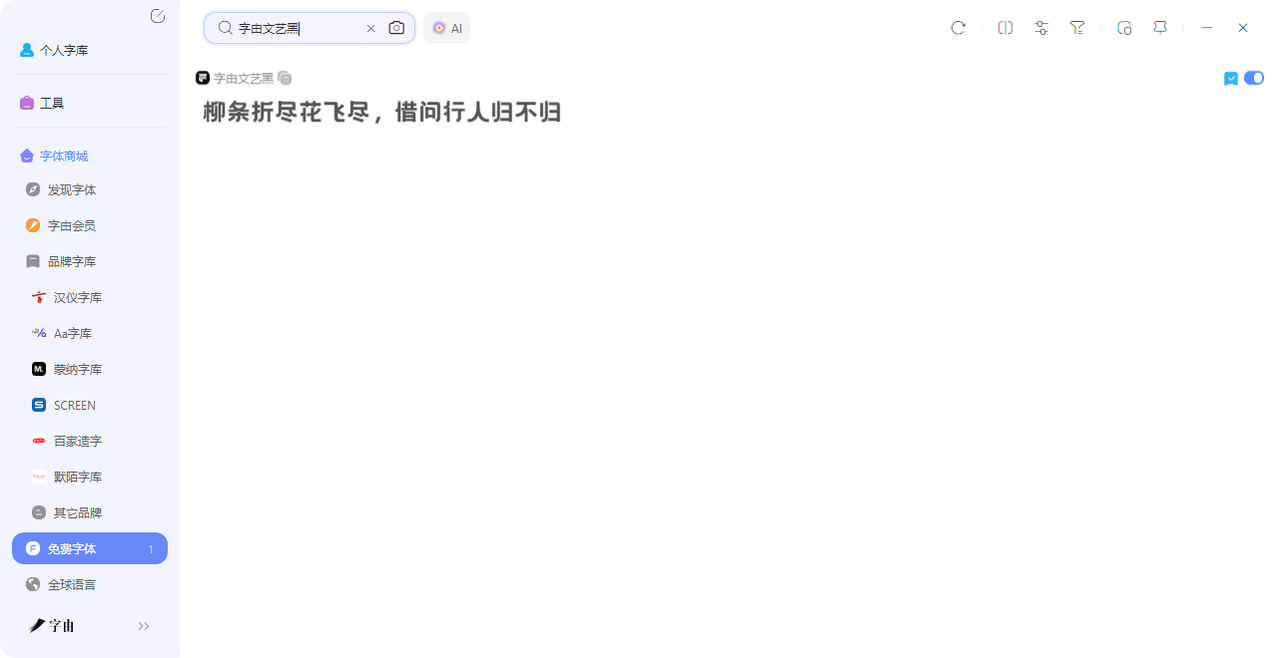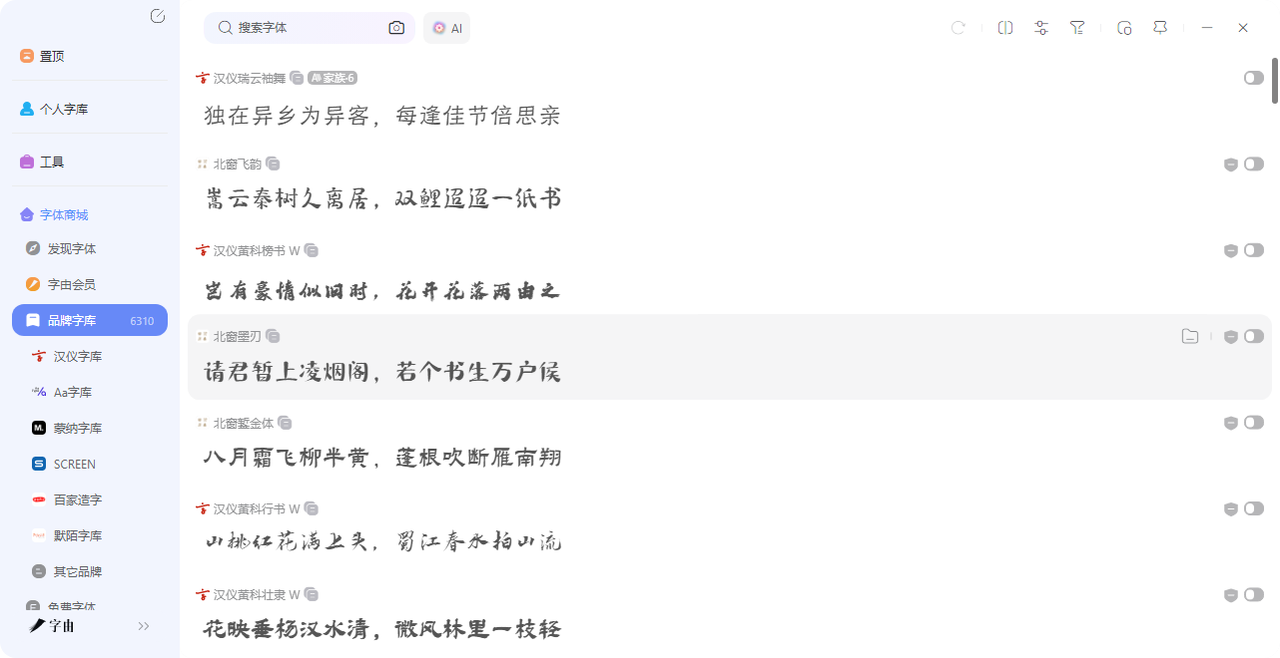
别再一个个下字体了!这几个打包下载网站直接收藏
做设计的人都知道,最烦的不是找字体,而是找着了之后一个一个下,麻烦的话还要给字体做收纳整理,遇到那种一个字体包里有好几个字重的,还得重复操作好几次。折腾半天,电脑里是多了几十款字体,但是时间也没了。其实,现在有不少网站支持字体打包下载,一次就能把整套字体收进电脑。今天我就把私藏的6 个字体打包下载网站分享出来,从国产神器字由到国外精选平台,每个都能让你省下大量时间。需要的直接收藏,以后下字体不用再一个个点。
很多人用字由,习惯一款一款点着用,但其实它有个更省事的思路——你不用下载,直接“打包用”。
字由的客户端里,目前已经有了3585 款免费商用字体。你不需要把每个字体文件下载到电脑里,而是打开客户端,选好字体,在PS 里点一下就能用。
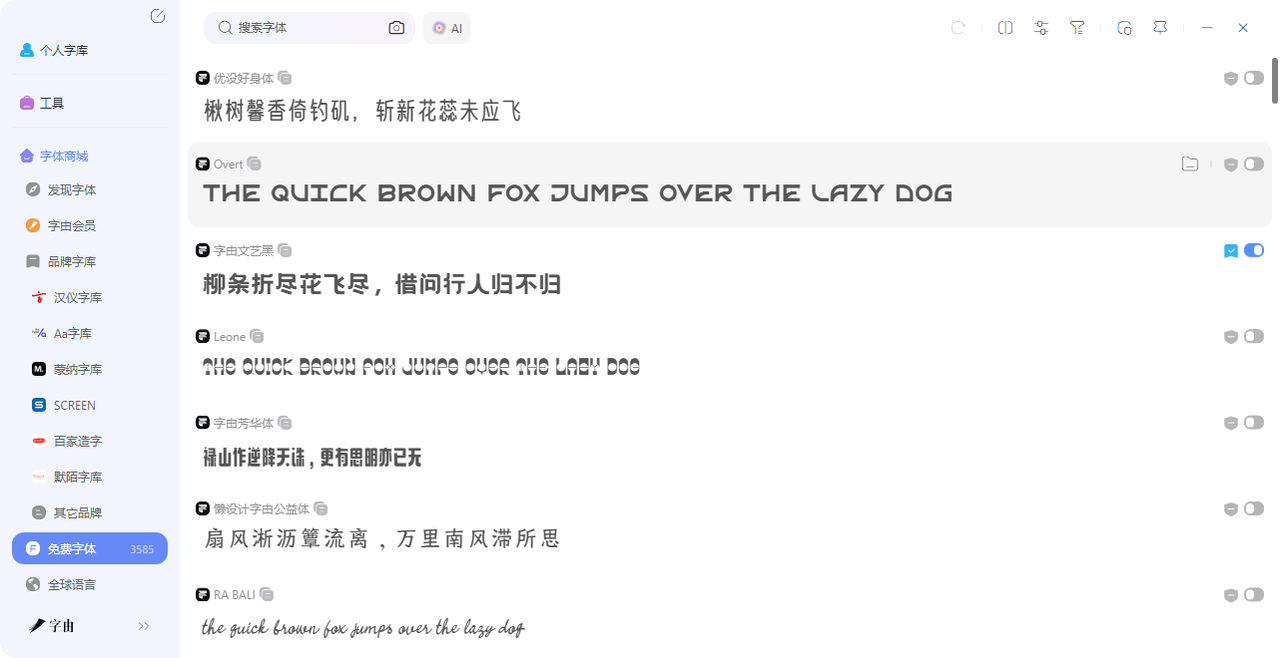
这相当于把几千款字体打包成了一个“在线字库”,随用随取,不用占硬盘空间,也不用一个个下载、解压、安装。
虽然这不叫“打包下载”,但本质上比打包下载更方便——因为你根本不需要下载。再加上个人云字库,这要比下载到电脑上方便得多。
下面我会推荐几款我比较喜欢用的免费可商用字体:
- 做海报标题的时候,我翻得最多的是字由文艺黑。它不像普通黑体那么死板,笔画里藏了一点手写的感觉。
- 做画册内页或者公众号配文,我习惯用优设好身体。字形方方正正,笔画不粗不细,排版起来很舒服。不会抢画面的风头,但细看又觉得挺耐看。
- 做旅行vlog的封面,我经常用点字浅夏体。227万次使用,笔画轻盈,像夏天傍晚的风。配上风景照,不用加什么特效,氛围就有了。
2、Packaging Fonts
这个设计资源平台它专门做了一个“Packaging Fonts”分类。这里的字体都是为包装设计准备的,风格偏商业、精致、有质感。页面左边有详细的筛选栏,可以按字体类型(Serif、Sans-Serif、Script)、字宽、大小来筛选。右边展示了9款推荐字体,比如“Habisa”(现代粗体手写)、“Street Beans”(街头风格)、“Candy Saga”(儿童包装字体)、“Pepperoni”(意式风格)等。这些字体大部分是付费的,但可以按需购买。它的“打包”体现在筛选逻辑上——你不需要在几千款字体里乱翻,直接在这里按风格、用途定位,找到合适的再下单。如果你做包装设计,这里是一个很好的灵感库和选字起点。
3、PACKAGING
PACKAGING 它没有复杂的筛选栏,而是直接把一款款字体摆出来,每款都有预览和基本信息。我数了一下,这一页展示了9款字体:
- Lemonaide Party:大写、小写、数字全都有,适合做柠檬主题的饮料包装
- Lemon Brownies:多语言支持,适合烘焙、甜品包装
- Baby Magpies:手写风格,适合儿童产品、玩具包装
- Grookey Shawn:圆润可爱,适合休闲食品
- Sally & Smith:复古衬线,适合精酿啤酒、手工制品
- Salista:4种字重,适合做品牌字体家族
- Esyla:城市主题,适合现代感强的产品
- Maleficent:暗黑风格,适合个性品牌
- Creative Designer:创意手写,适合设计师个人品牌
每款字体都有下载入口,可以单独下,也可以把这一页当成“打包推荐”——一口气看9 款,看中哪个下哪个。这种集合页的好处是,你不用自己翻分类,人家帮你把适合包装的字体挑好了,你只需要挑自己喜欢的。
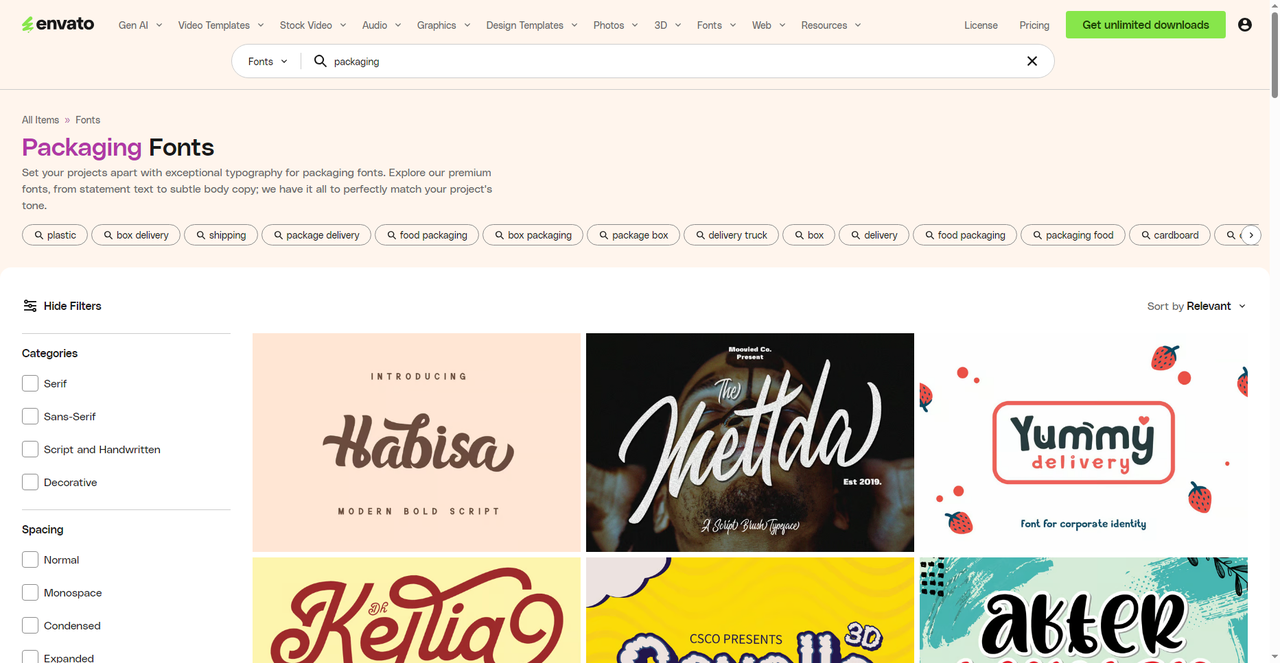
4、Fontsc – 110
Fontsc网站的“Packaging Fonts”分类,它一共收录了110款适合包装设计的字体,每款都标注了授权类型。页面顶部的筛选栏很实用:
- Sort By Popular:按热度排序,优先看别人用得多的
- List 10 Fonts:可以选择每页显示多少款
这里我会推荐的几款字体:
- Built Titling:无衬线体,适合标题
- Allura Regular:优雅手写体,SIL OFL授权,免费商用
- Champignon:法式花体,免费个人及商用
- Steelfish:工业感无衬线,6种字重,适合硬朗风格
- Poiret One:现代简约,适合极简包装
Fontsc 的“打包”体现在筛选上——你可以先按“Commercial Free Only”筛一遍,剩下全是免费商用的,然后按热度排序,挑下载次数高的,一口气点“DOWNLOAD”下好几款。不用一个个翻授权说明,省事很多。
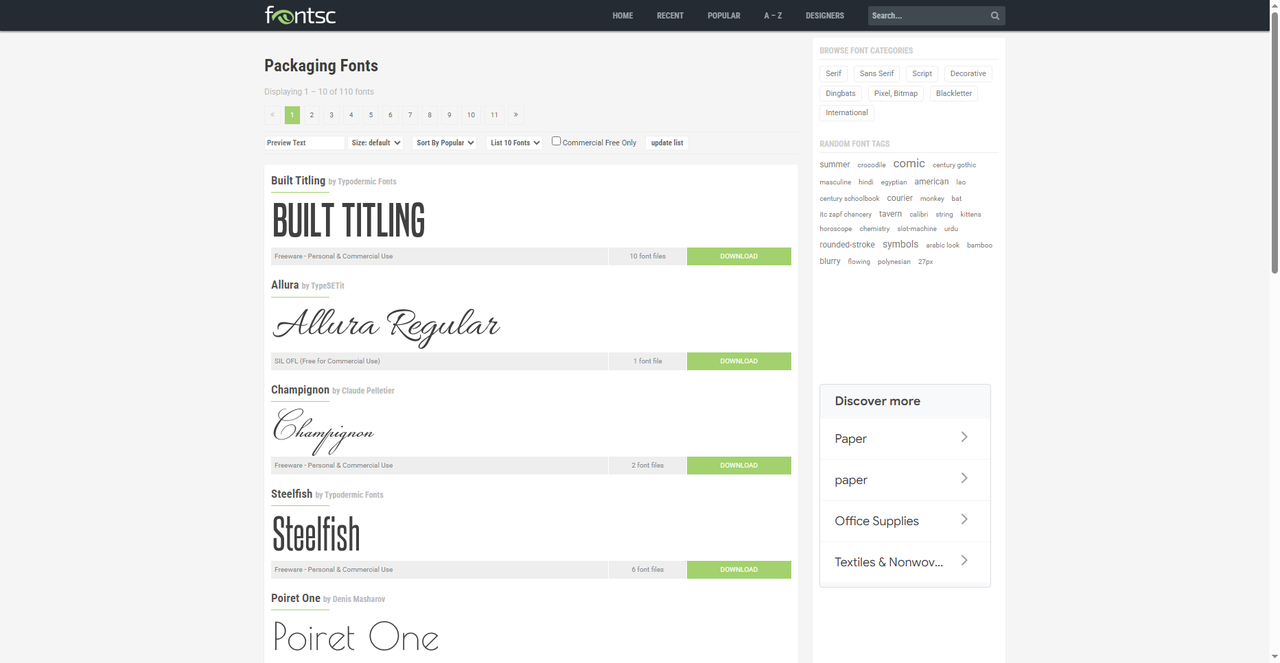
5、29 Best Free Packaging Fonts
第四张截图是一个精选合集,叫“29 Best Free Packaging Fonts”。它从Google Fonts里挑了29款最适合包装设计的免费字体,每款都标注了推荐理由、分类、人气、趋势。页面顶部有预览框,可以输入你的文字,实时看效果。字体大小、粗细、样式都能调。推荐的第一款是Montserrat:几何无衬线,现代感强,适合产品信息排版。人气7,趋势1238。第二款是Lato:温暖友好的无衬线,可读性好,适合配料表、产品描述。人气9,趋势1486。第三款是Roboto:经典无衬线,简洁清晰,适合任何包装上的正文文字。
这个合集本身就是一种“打包”——人家把29款好用的免费字体打包在一起,你只需要点开页面,看预览,喜欢就下载。不用自己从几千款Google Fonts 里慢慢挑,省了90% 的筛选时间。